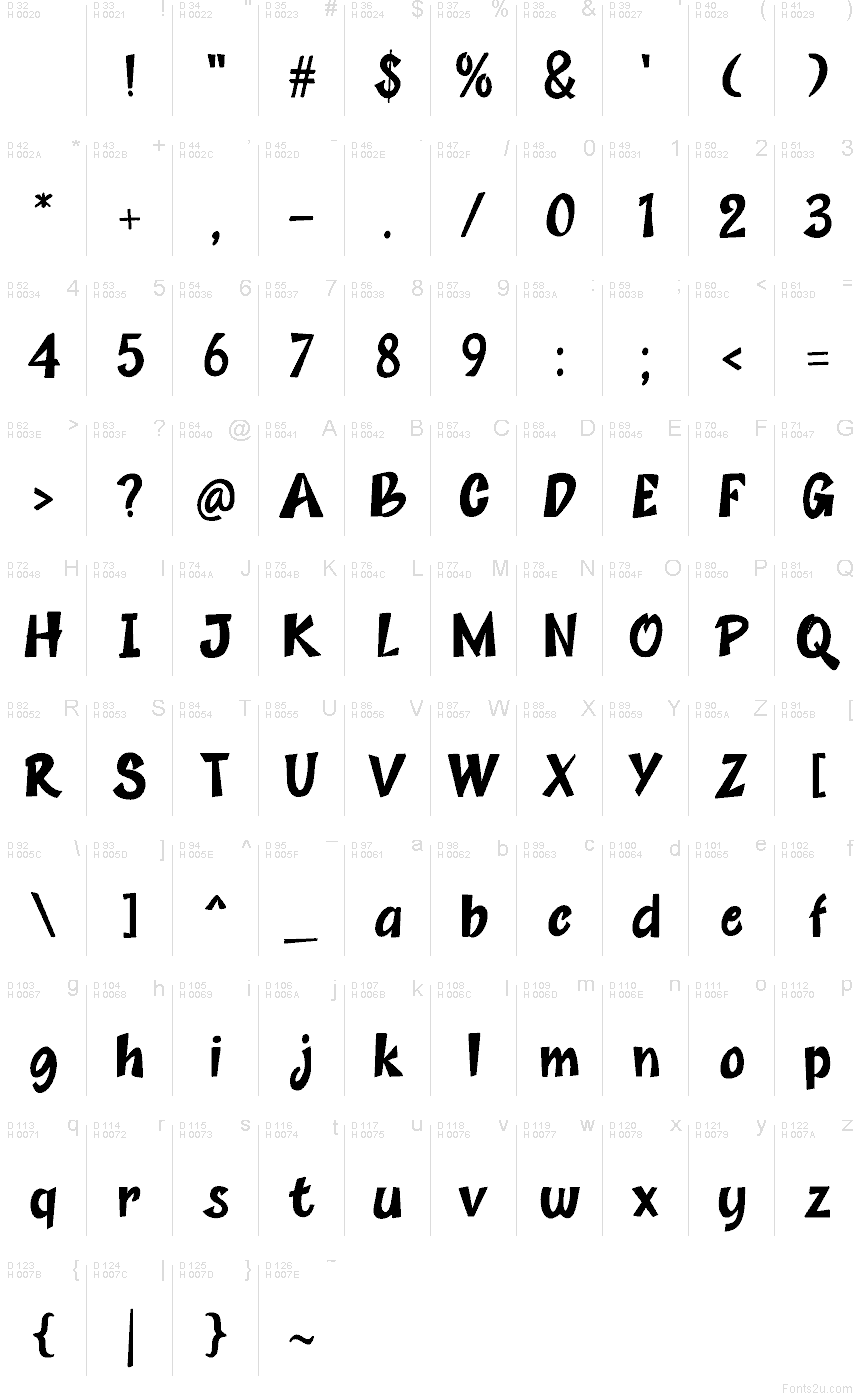
Solid Newborn від Hello Good Studio - це безкоштовний акцидентний шрифт у коміксному стилі з округлими формами та впевненим «ручним» ритмом. Літери мають приємну нерівність, поєднуючи м’які вигини, компактний кернінг та кілька чітких зрізів, що не дають дизайну виглядати надто вигладженим.
Solid Newborn чудово підходить для дитячих плакатів, грайливих логотипів, коміксних заголовків, пакування та графіки для соцмереж, адже його округлі форми залишаються виразними, не будучи при цьому перевантаженими. Цей безкоштовний шрифт також стане в пригоді для етикеток товарів, наклейок та коротких банерів, де ви шукаєте дружній, характерний стиль, що зберігає впевненість та стійкість.